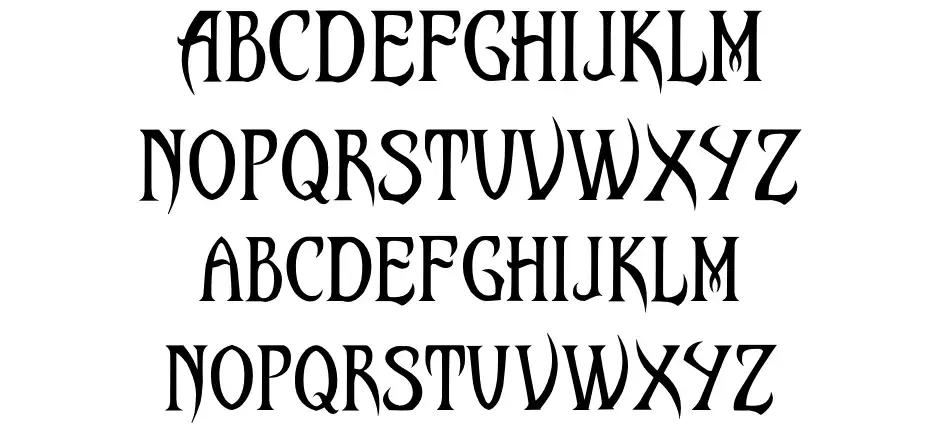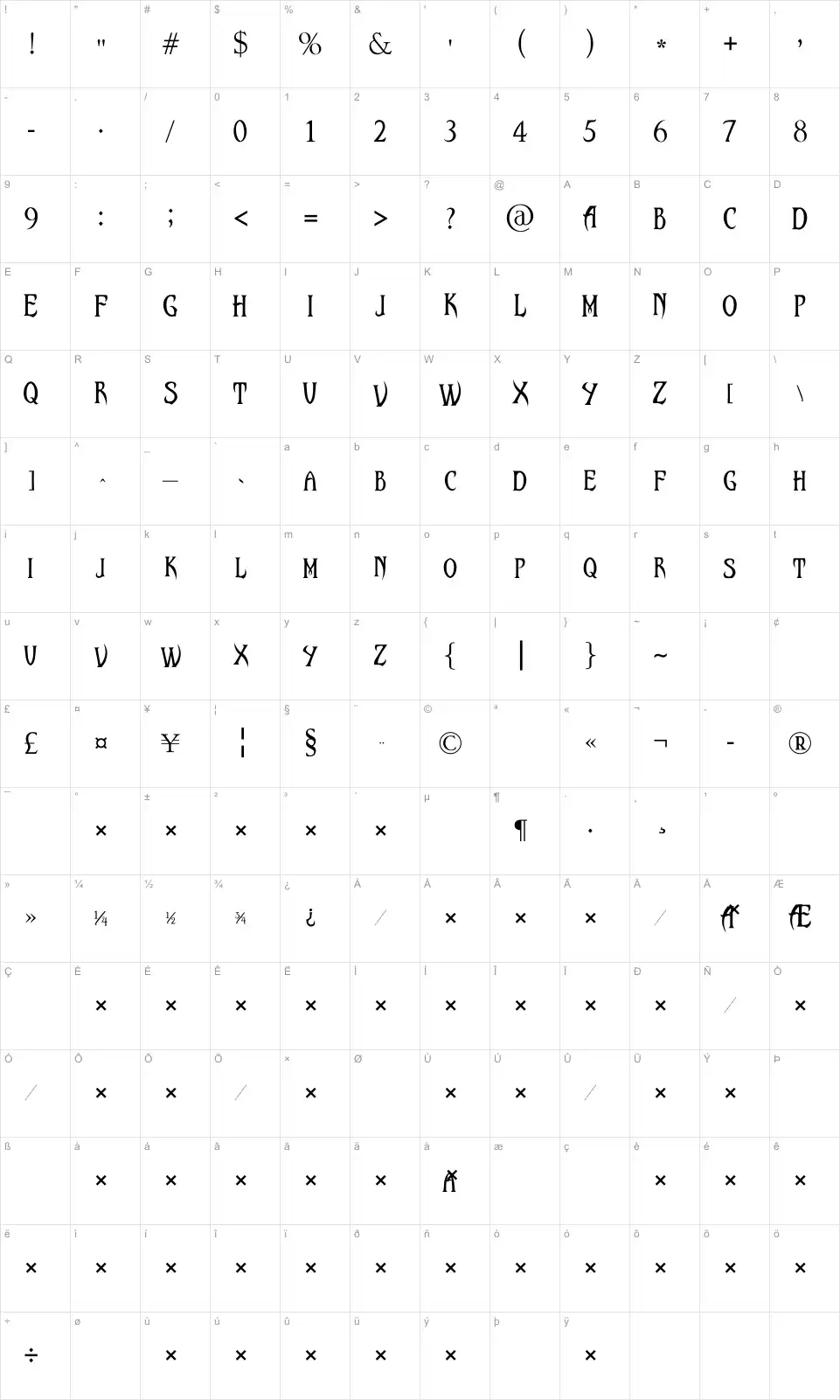
Malefic Font – Download Grátis
A fonte ‘Malefic Font’, criada pela designer Jennifer Zaiku, é uma escolha perfeita para qualquer projeto que busque um estilo gothic e distorcido. Esta fonte é gratuita para uso pessoal e está disponível em formato TTF, tornando-a facilmente integrável em qualquer projeto digital. Com sua categoria em Gothic, a ‘Malefic Font’ combina exatamente o que você precisa para dar um toque único e memorável a seus materiais. Adicionada em julho de 2022, a ‘Malefic Font’ já recebeu 2214 downloads, o que demonstra a sua popularidade e qualidade. Se você está procurando por um texto personalizado para testar essa fonte antes de implementá-la, pode fazer isso online gratuitamente. Este é um excelente ponto de partida para aqueles que buscam um estilo mais distorcido e criativo em seus designs.
Designer: Jeniffer Zaiku